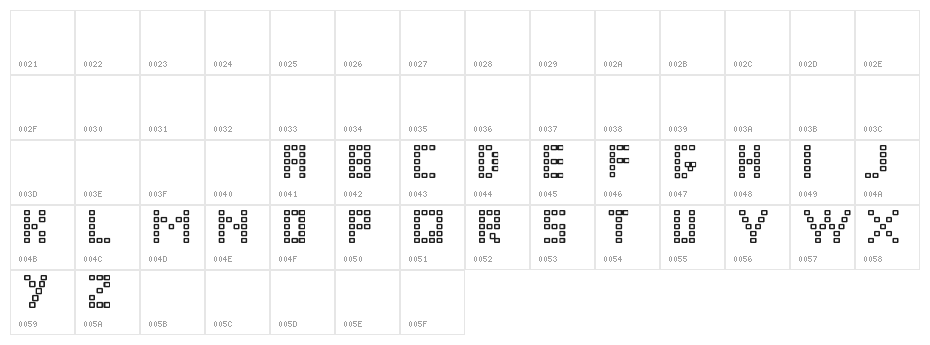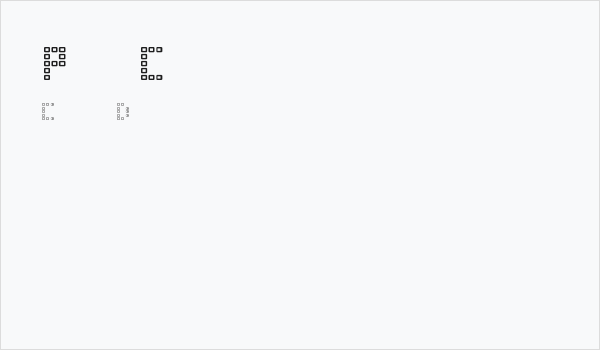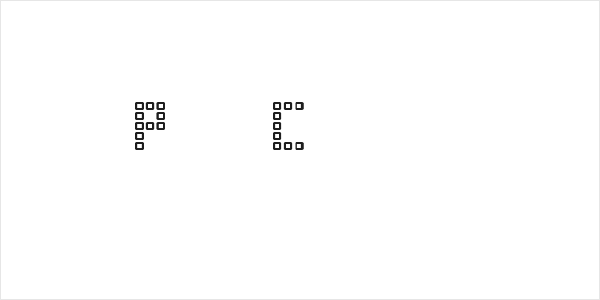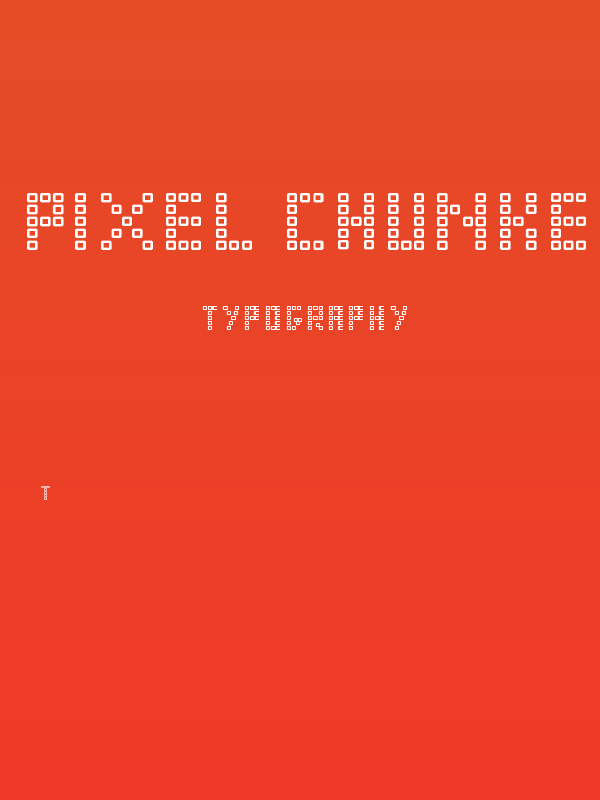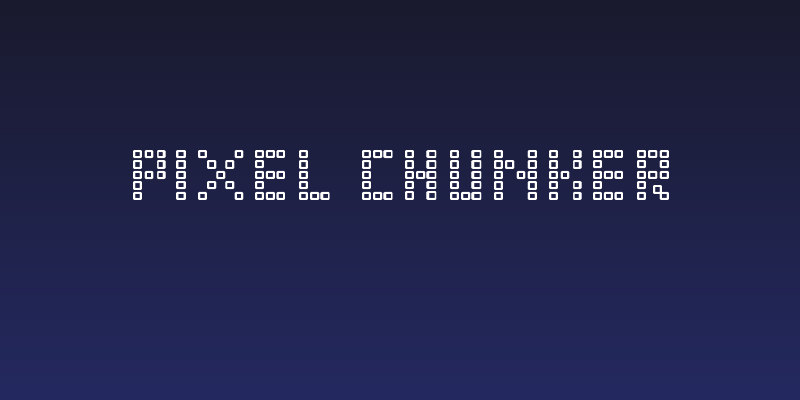
Pixel-Chunker Font
✎ Dotted
| Name | Pixel-Chunker |
| Kategorien | Dotted |
| Gesamtstil | Retro, Digital |
| Anwendungsfall | Headlines, Logos, Digital Art |
| Vorgeschlagene Projekte | Ideal for video game design, tech-themed posters, digital art projects, and retro-style branding. |